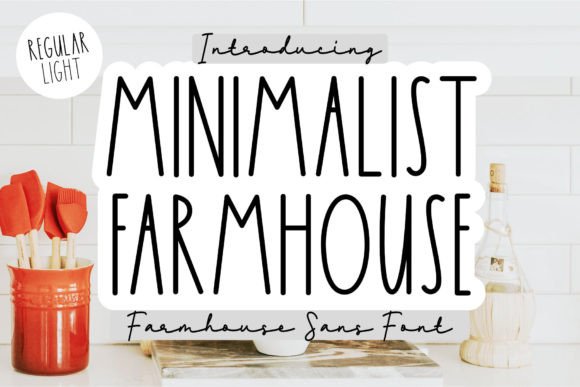
Minimalist Farmhouse
Znalezienie odpowiednich elementów projektu może być wyzwaniem, ale Minimalist Farmhouse oferuje wyjątkową kolekcję, która natychmiast ulepszy Twoją pracę.
Niezależnie od tego, czy tworzysz produkty POD (druk na żądanie), zaproszenia ślubne czy grafiki do mediów społecznościowych, Minimalist Farmhouse będzie idealnym wyborem.